Квадратная хоральная нотация: как читать знаки и собрать точный макет
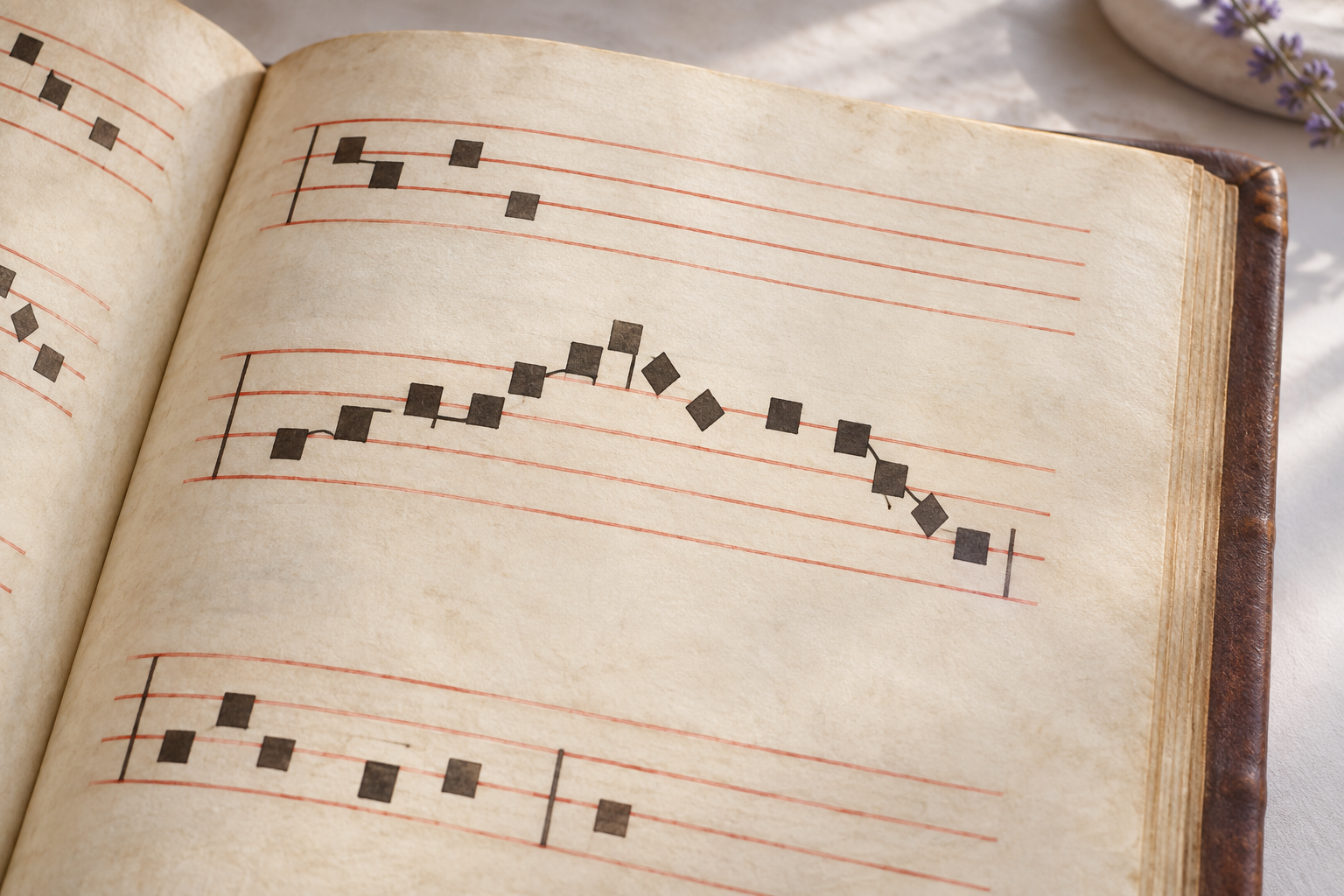
Квадратная хоральная нотация — способ записывать одноголосное церковное пение квадратными и ромбовидными нотными знаками на линейном стане. Чтобы распознать её в рукописи и аккуратно использовать в современном макете, смотрите не только на «квадратики»: важны число и цвет линий, ключ, связь знаков со слогами, интервалы между группами и подсказки на краю строки. Ниже — маршрут от наблюдения до проверенной пробной полосы.
Сначала определите, что именно перед вами
Квадратная нотация выглядит узнаваемо: чёрные угловатые головки стоят над латинским текстом, обычно на линейном стане. Но одного внешнего сходства недостаточно, чтобы назвать страницу старинным хоралом. Сопоставьте сразу три признака: расположение нот по высоте, систему линий и отношение музыкальных групп к слогам. Рукописный источник может включать и текстовые рубрики, цветные линии, украшенные инициалы; эти элементы тоже влияют на композицию.
Так называют целое семейство практик записи хоральной мелодии, а не один неизменный шрифт. Каталог Библиотеки Конгресса описывает развитие литургических рукописей от ранних невм без стана и с линейками до нотных головок квадратной формы. Оцифрованный фрагмент из той же коллекции датирован широко — между XI и XII веками по каталогу — и описан как пергамент с квадратными невмами, черными чернилами и рубриками и инициалами красного и синего цвета. Эти записи полезны как проверяемые примеры, но конкретный лист всегда важнее обобщённого «средневекового стиля».
Для дизайнера главный вопрос звучит практично: вы стилизуете страницу с узнаваемыми знаками, готовите точную транскрипцию конкретного фрагмента или строите декоративный мотив по его ритму? Это три разных задачи. В первом случае достаточно корректно передать визуальные признаки; во втором нужно сверять каждую ноту и текст с источником; в третьем нельзя выдавать орнамент за подлинную музыкальную запись.
Прочитайте стан и ключ до того, как рисовать ноты
Линии дают нотам опорные позиции по высоте. В типичных хоральных источниках встречается четырёхлинейный стан, но это не универсальное правило для любого времени и места. Например, каталог Антифонария для утрени из собрания Чикагского университета описывает испанскую рукопись XVI или XVII века с квадратной нотацией на пятилинейном стане. В фондах Университета Пенсильвании есть книга песнопений, где соседствуют страницы на четырёх и пяти линиях. Поэтому число линеек — наблюдение о конкретном объекте, а не тест на «подлинность».
Найдите ключ: его положение задаёт, какая линия служит ориентиром для чтения высоты. В хоральной записи встречаются ключи C и F; их положение на стане может меняться. Не копируйте значок ключа из другого образца в привычное место и не считайте линию автоматически «до» или «фа»: сначала установите позицию ключа именно на этой странице. Если ваша задача — декоративная реконструкция, отметьте ключ как отдельный обязательный элемент; если мелодическая точность не нужна, всё равно не превращайте его в случайный орнамент.
Проверьте цвет и толщину линеек. В рукописях линии могли быть проведены красным или другим контрастным пигментом; иногда одна линейка отличается от остальных. Не усиливайте этот сигнал без источника: красная полоса на иллюстрации может быть поздней разметкой, реставрационным следом или особенностью конкретной книги. Для точного макета зафиксируйте цвет каждой линии по фотографии, включая выцветание, а потом решите, воспроизводите ли вы оригинальное состояние или делаете чистую учебную версию.
Разберите форму ноты и не путайте её с длительностью
Простая квадратная головка часто называется пунктумом. Вертикальная черта у головки даёт форму, которую называют виргой. В группах две или несколько нот соединяются в единый графический жест: например, восходящий податус (pes) и нисходящий кливис. На конкретном письме такие группы могут выглядеть по-разному — меняются наклон, соединение штрихов, расстояние и степень угловатости. Не стоит сводить их к универсальным пиктограммам: рассматривайте несколько примеров одного знака в одном источнике.
Название формы ещё не объясняет всё звучание. Квадратная запись показывает высотное движение и группировку мелодии, но по одному контуру ноты нельзя автоматически вывести точную длительность в современных долях. Пение хорала связано с текстом, фразировкой и традицией исполнения; современные тактовые черты и метрономическая сетка не должны появляться в реконструкции «по привычке». Если нужно музыкально исполнить мелодию, сверяйтесь с принятой транскрипцией или специалистом по источнику, а не с декоративной картинкой.
Отдельно изучите знаки, которые легко принять за ноту. Кустос — маленькая подсказка у края системы о высоте следующей строки; он не заменяет первую ноту нового стана и не должен случайно попадать внутрь такта. Паузы и разделители тоже читаются в контексте: вертикальная черта в источнике может работать как граница фразы, но не обязательно соответствует современной тактовой черте. Для макета полезно выписать каждый знак из выбранной страницы в отдельную таблицу: форма, положение, функция, уверенность в распознавании.